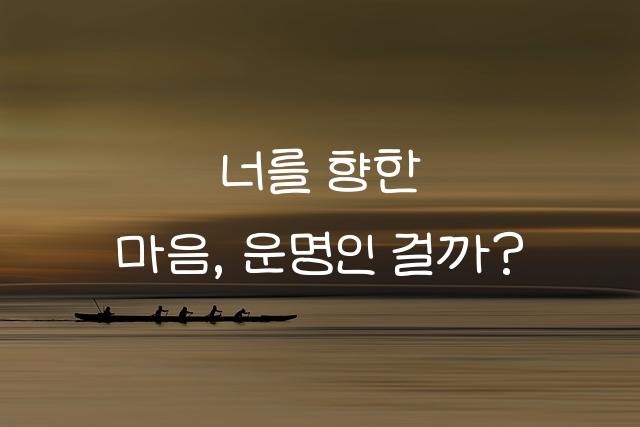
심경하체는 흥국생명에 의해 제작된 한글 폰트로, 또박또박하고 정갈한 어른의 손글씨 스타일을 담고 있습니다. 이 폰트는 부드러움과 세련됨을 겸비하여 감성적인 텍스트 표현에 적합합니다.
심경하체은(는)
바탕 스타일, 손글씨, 감성적인, 부드러움 계열의 생김새를 가지고 있으며
초대장, 인사말 카드, 일기/편지 등에서 자주 활용되며, 효과적인 메시지 전달에 적합합니다.
이 폰트는 라이프스타일, 문화/예술, 이벤트/웨딩 분야에 잘 어울리며,
친근한, 감성적인, 편안한 느낌을 담고 있는 것이 특징입니다.